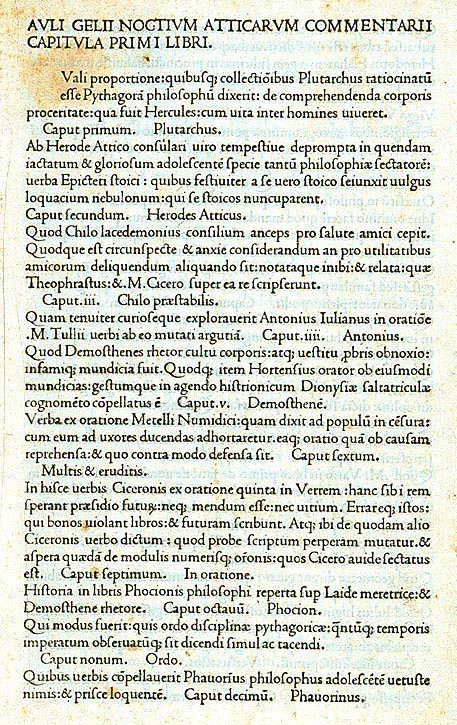
Nicolas Jenson (1420-1480)De Mainz para Veneza: Quando o francês Nicolas Jenson adaptou melhor a littera antiqua dos calígrafos para os tipos de chumbo, criou um padrão de letra que iria prevalecer até hoje.Natural de Troyes, Jenson fora enviado em 1458 por Charles VII a Mainz, para espiar o segredo da impressão mecânica com tipos móveis - a invenção de Johannes Gutenberg. Quando regressou da Alemanha, em posse do novo saber, o descendente de Charles VII já não manifestou qualquer interesse pelo assunto. Jenson virou as costas à França e emigrou para Veneza, onde se tornou concorrente dos irmãos Speyer. A partir de 1468, Jenson trabalhou em Veneza como gravador de punções, impressor e editor. Produziu cerca de 150 edições; os livros impressos entre 1470 e 1480 (ano da sua morte) têm servido de fonte de inspiração a inúmeros typeface designers posteriores, como veremos adiante. Jenson adquirira o seu knowhow na fonte, pois trabalhou como aprendiz na oficina de Johannes Gutenberg em Mainz. Mas a inspiração estética da sua letra teria vindo da lendária Coluna de Trajano. Passados cerca de 25 anos da invenção de Gutenberg (cerca de 1455), Jenson gravou em 1470 os punções dum novo tipo metálico de romanas. O antigo discípulo de Johannes Gutenberg estava bem preparado, pois fora assessorado tecnicamente por dois ex-colegas da época de Mainz: Sweynheim e Pannartz. A combinação da tecnologia alemã com a estética italiana não poderia ter sido mais afortunada. O grande feito tipográfico do franco-veneziano Nicolas Jenson foi a realização em chumbo de um alfabeto misto a littera antiqua tipográfica. Ao gosto dos humanistas italianos, harmonizou letras de proveniências diferentes. As maiúsculas lapidares da Capitalis Quadrata foram complementadas com minúsculas humanistas, por sua vez derivadas da letra carolina.
Muito em breve, outros prototipógrafos iriam suceder a Jenson, obscurecendo-lhe a fama na fervilhante cidade de Veneza. Aí foram Ratdolt e o editor Manutius que deram à antiqua humanista a forma consumada que perdurou até hoje. þ